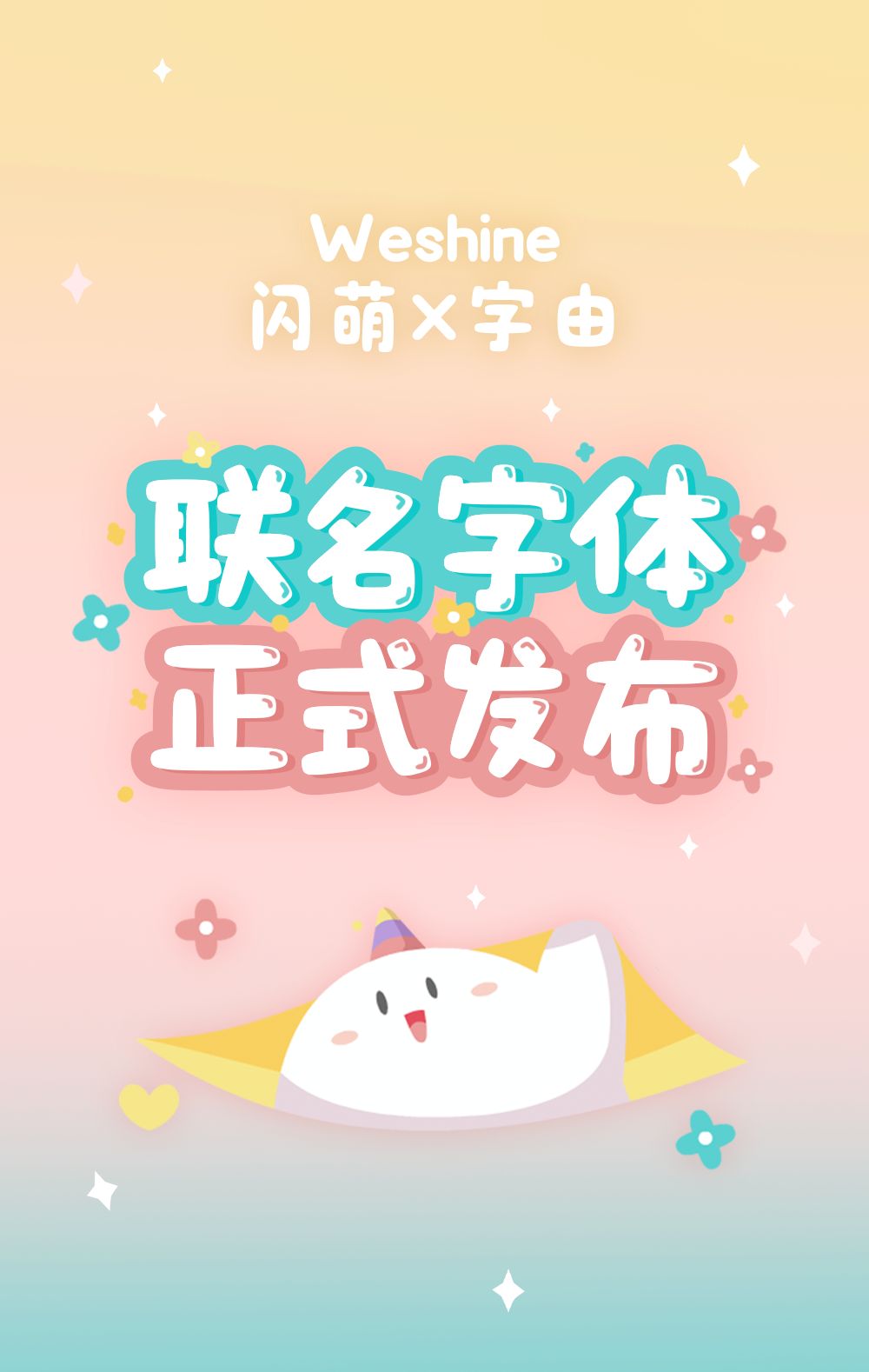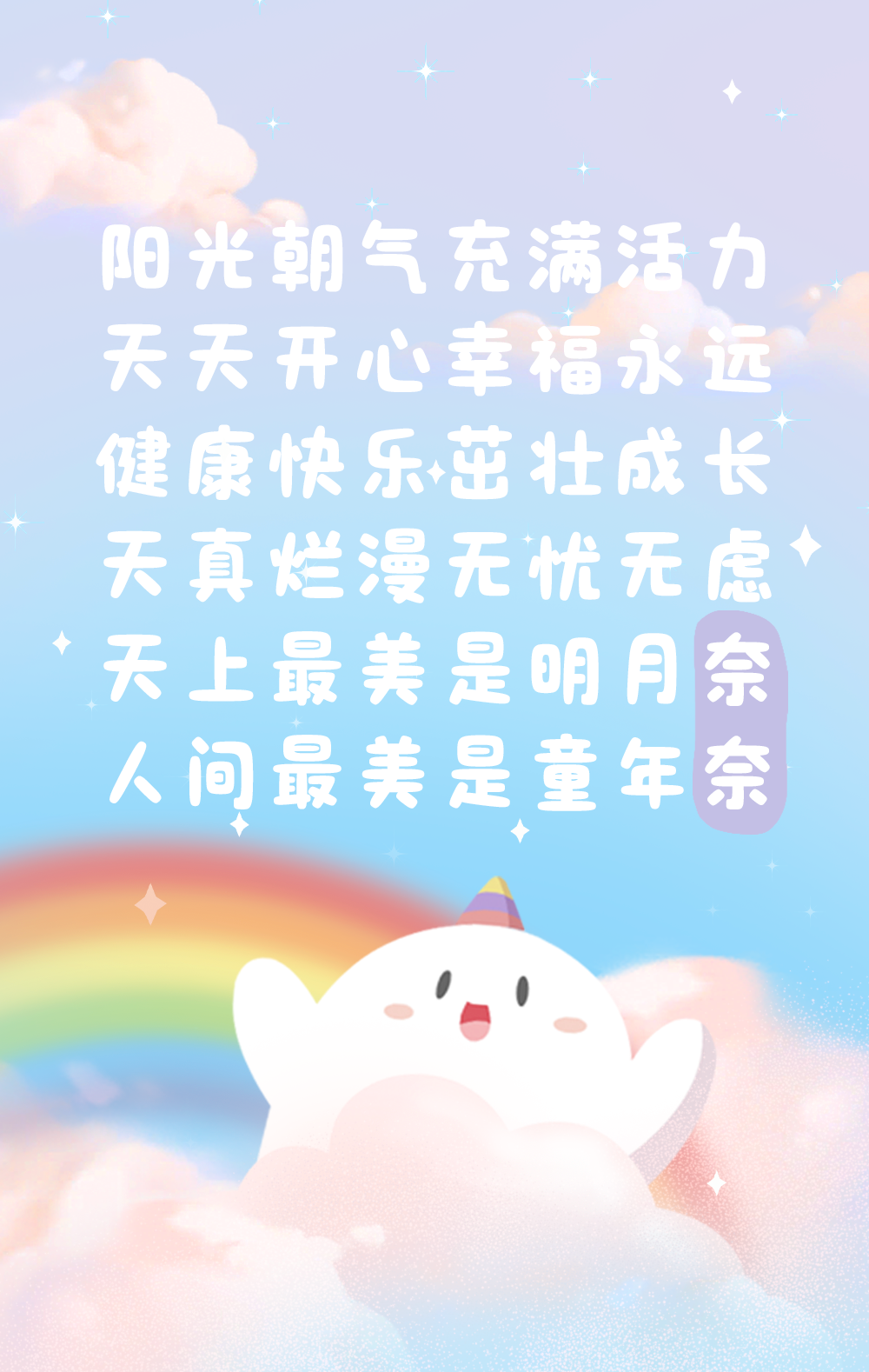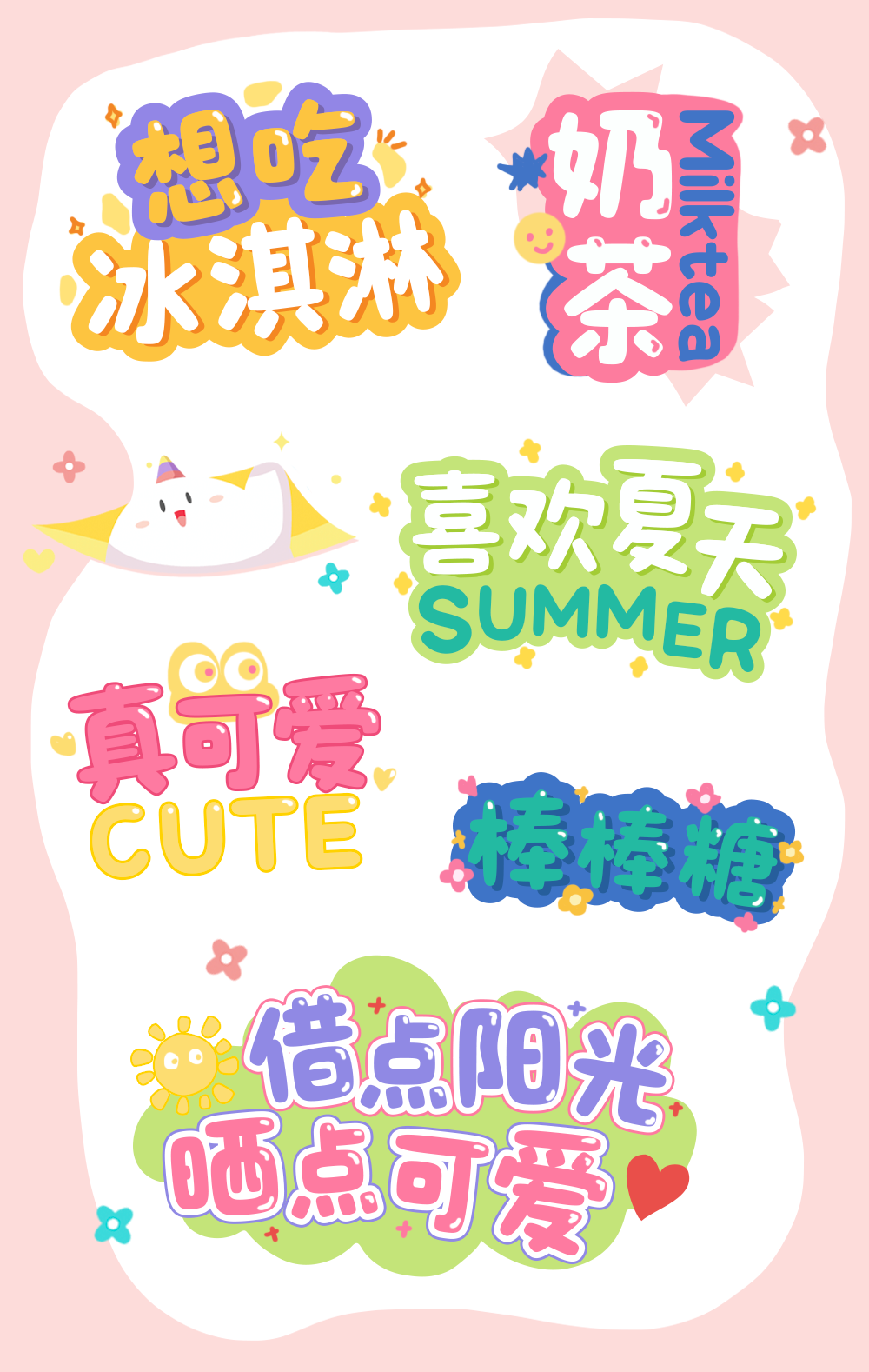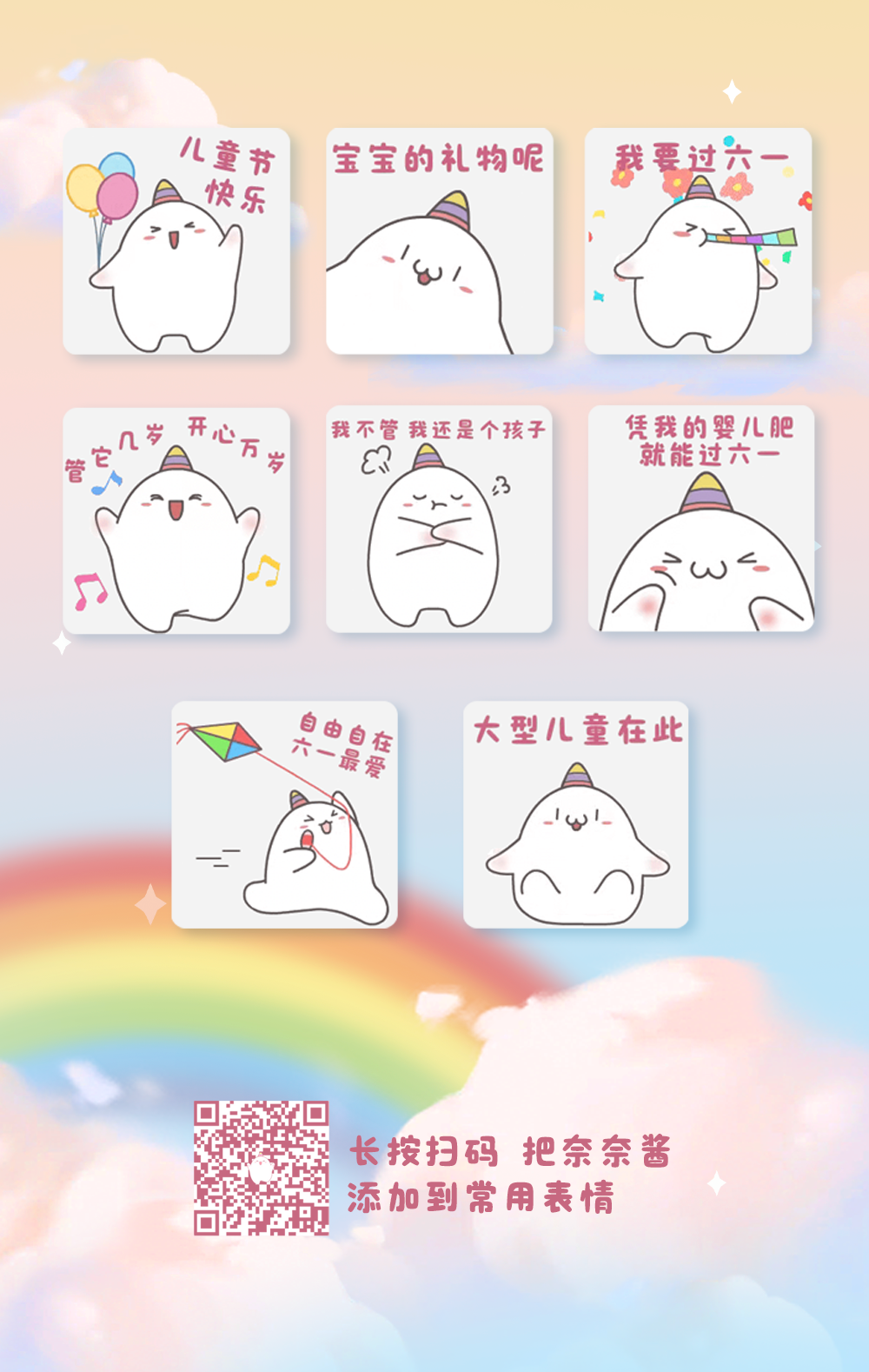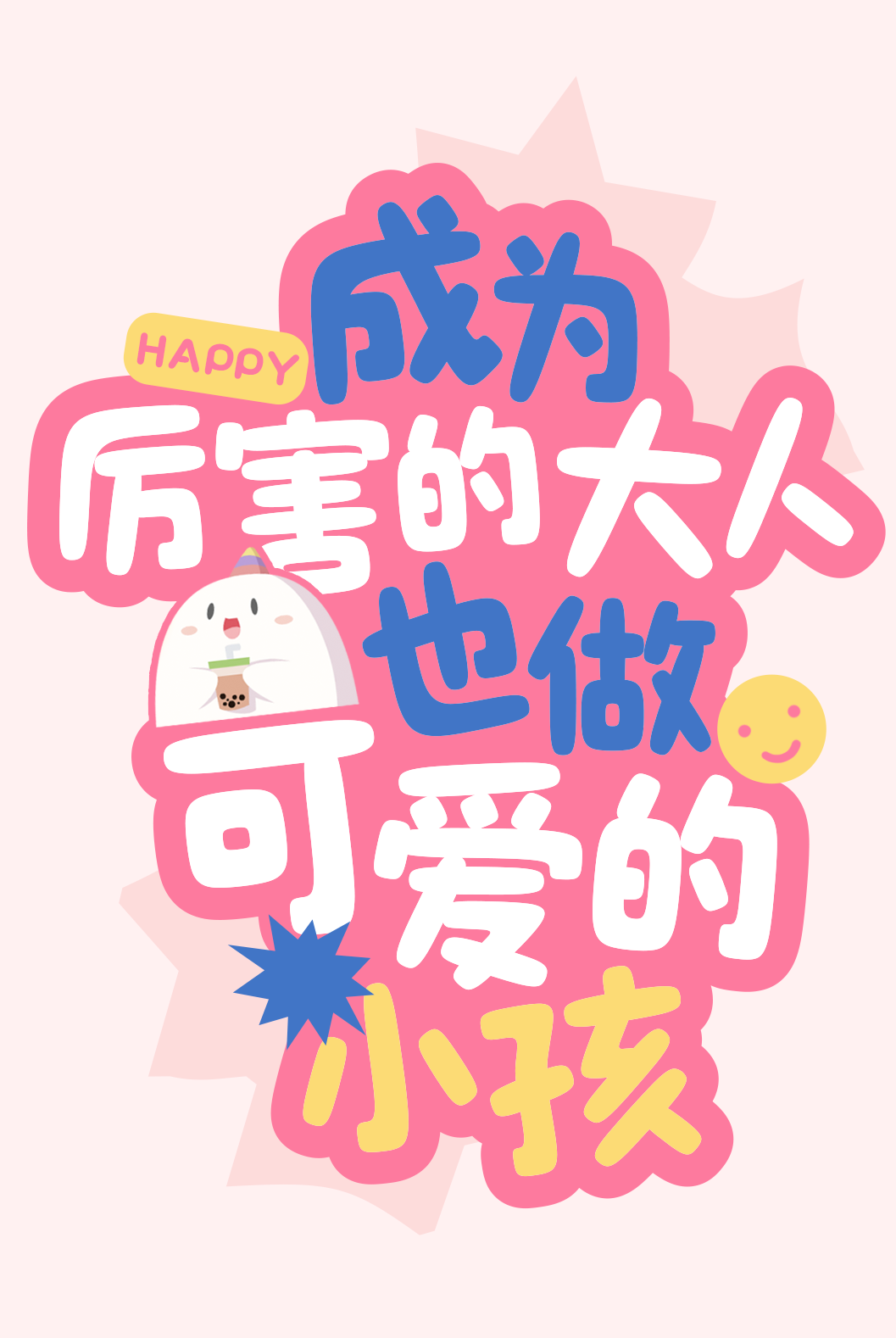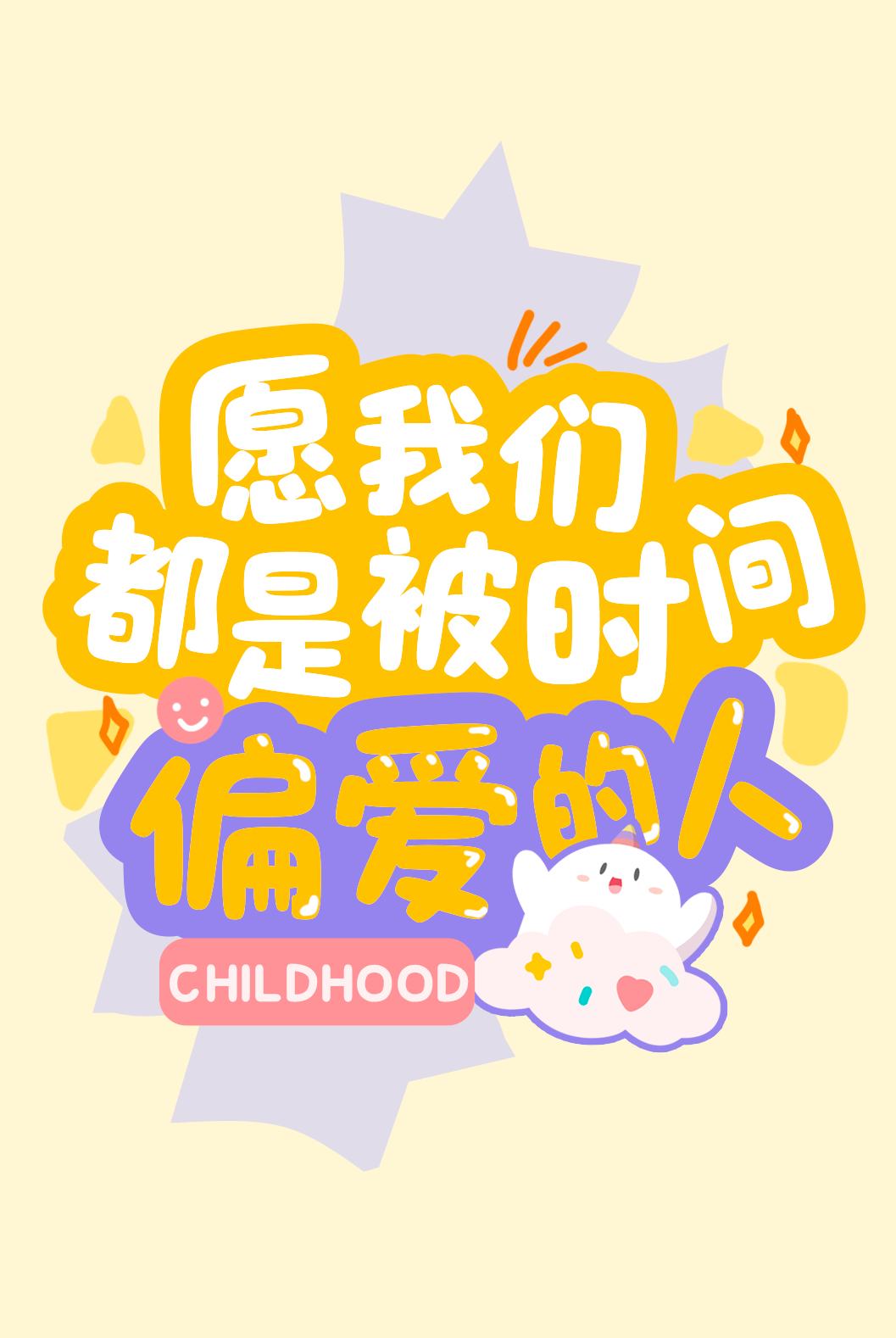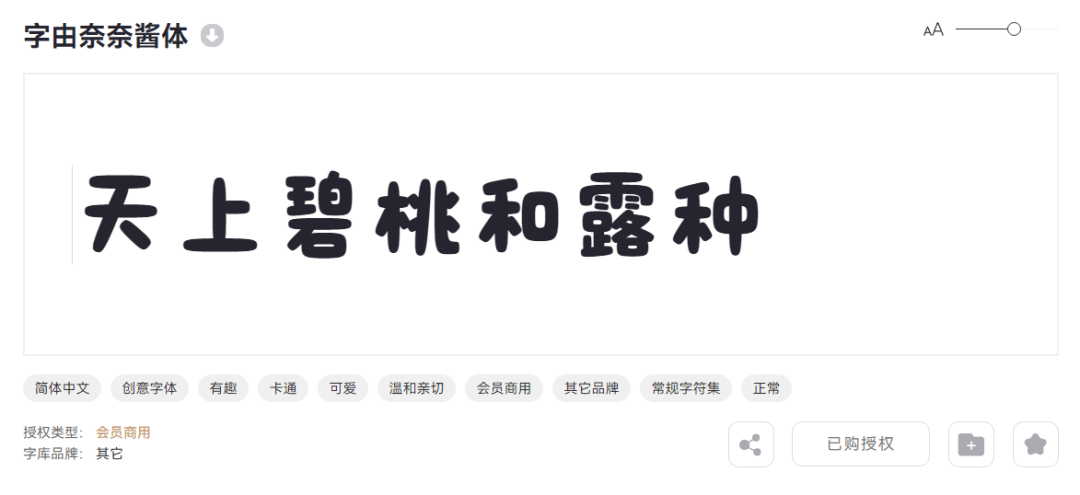
大儿童的快乐字体,字由奈奈酱来啦!
旗下经典的IP形象——“独角兽奈奈酱”,天真烂漫,饱满圆润,看起来特别好rua~
如今它也有专属字体了,就是这个字由奈奈酱体。
字体线条跟“独角兽奈奈酱”一样,又软、又圆、又滑、又萌~
把它用在美食场景,再合适不过了,看起来就很甜~
用做表情包,也是满满的亲和力,一秒破功~
当然,用来做海报标题字,奈奈酱也是毫不逊色,挪不开眼的存在。